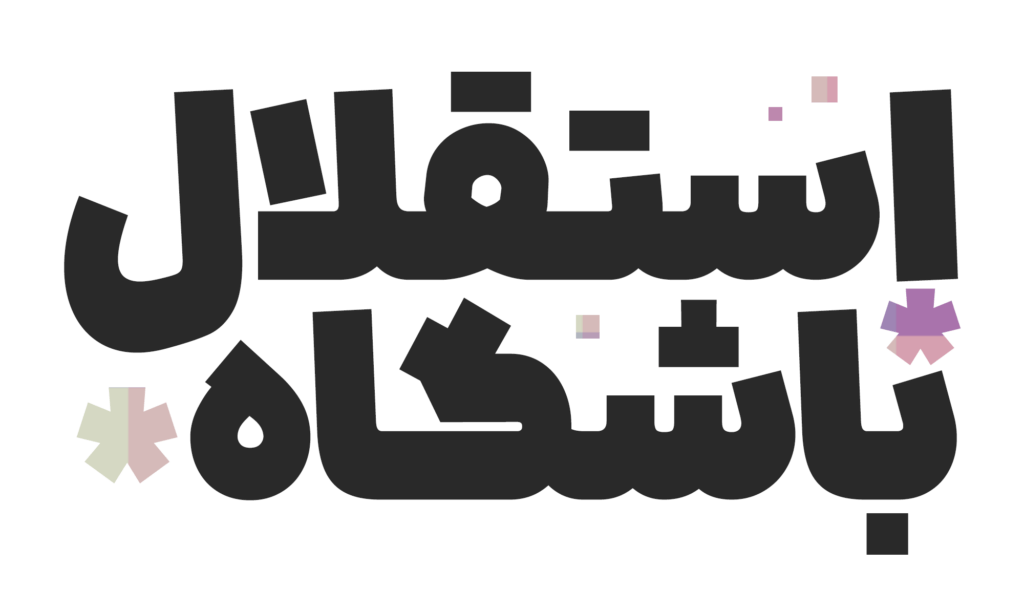
خانواده فونت دانا
Dana
دانا فونتی فارسی با شخصیت آرام، متعادل و مدرن است که برای برندهایی با هویت مینیمال و حرفه‌ای بسیار مناسب به نظر می‌رسد. فرم‌های نرم و کنترل‌شده این فونت باعث می‌شود در طراحی لوگوتایپ، حس نظم و اعتماد را به خوبی منتقل کند. دانا برای برندهایی که می‌خواهند ظاهرشان ساده اما دقیق و خوش‌ساخت باشد، انتخاب خوبی است.
روی نرم‌تر کردن برخی گوشه‌ها، اصلاح فاصله‌ها و ایجاد ریتم بهتر در حروف تمرکز می‌کنم تا لوگوتایپ نهایی هم خوانا باشد و هم شخصیت بصری بیشتری پیدا کند.